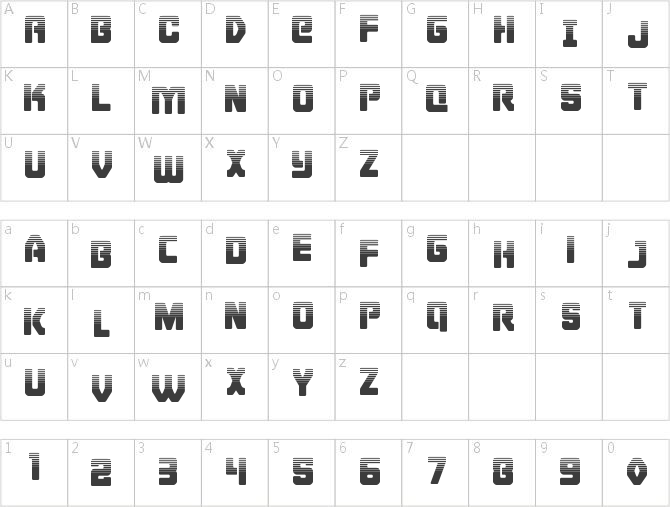
cyborgroosterhalf
cyborgroosterhalf介紹
cyborgroosterhalf字體字庫是一款讓人賞心悅目、百看不厭的英文字體,適合各類廣告和產(chǎn)品包裝設(shè)計應(yīng)用,字體大小0.06MB,格式為ttf字體,上傳用戶是@小咖,作者/版權(quán)方為未知